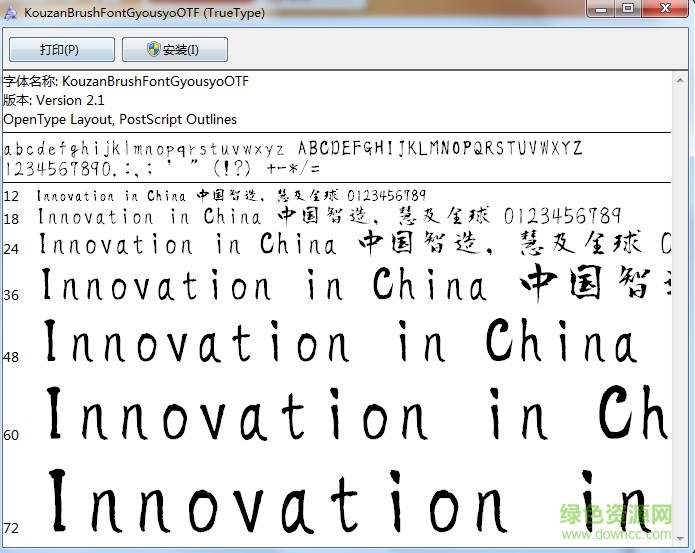
衡山毛筆行書
衡山毛筆行書是日本書法家衡山先生新推出的行書字體,采用毛筆書法制成,行文流暢字跡優(yōu)雅,造型別致,適合于廣告設(shè)計(jì)、排版印刷等行業(yè),歡迎大家來綠色資源網(wǎng)免費(fèi)下載!
衡山毛筆行書字體介紹
衡山毛筆行書有日本青柳衡山先生所創(chuàng),支持繁體輸入,部分字體簡(jiǎn)體無(wú)法顯示,需將其轉(zhuǎn)換成繁體文字!
衡山毛筆行書繁體
衡山毛筆行書作為一款日系中文字體,暫且支持繁體中文,字體完整不缺字,安裝后字體名稱為KouzanBrushFontGyousyoOTF,歡迎使用!